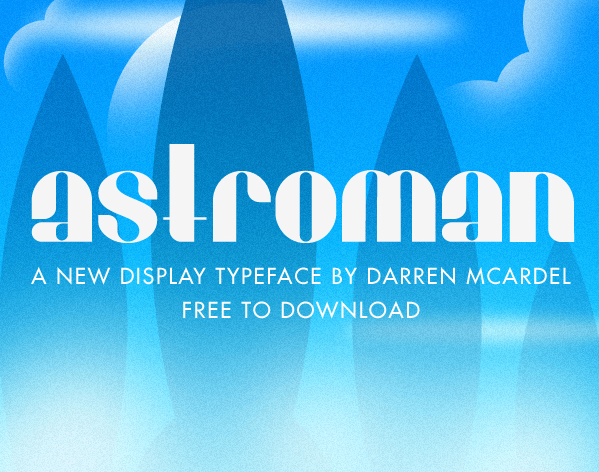
Astroman Typeface – Download Grátis
Astroman é uma fonte criada pelo designer Darren McArdel, de Seattle na USA. Inspirada nos enredos fantásticos da ciência-ficção e misturada com características retro, ela traz linhas estilizadas que são desiguais e altamente distintas. Esta fonte exalta uma vibe futurista e é ideal para projetos como animações, filmes explorando o universo ou qualquer projeto gráfico que busque um estilo espacial único e inovador. Como uma fonte do tipo Display, Astroman oferece linhas definidas e estilizadas perfeitas para destacar textos em mídias visuais. Seja você um designer de animação, cineasta explorando o universo ou criativo buscando expressar seu trabalho de forma visualmente avassaladora, Astorman é a fonte certa para iluminar seus projetos.